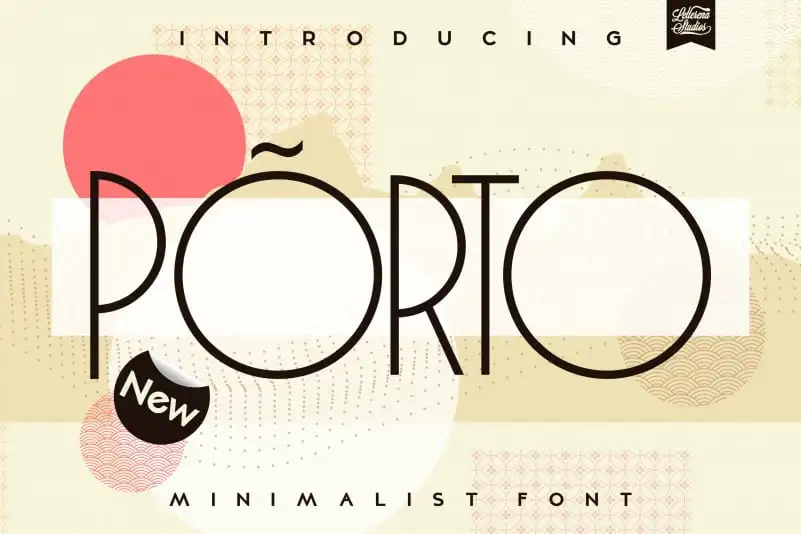
A Porto Display Font é uma escolha perfeita para quem busca um estilo moderno e clean no design de sem-serif. Ela traz letras leves e agradáveis ao olho, com uma aparência muito arredondada que se assemelha mais às serifas do que aos verdadeiros sem-serais. Com sua textura limpa e fina, essa fonte tem um toque suave que permite destacar seu conteúdo de maneira sofisticada. Os criadores da letra, a Letterenastudios, certamente não poderiam ter previsto o sucesso dessa fonte em qualquer projeto gráfico. Seja ela usada em design web, impressão ou aplicativos móveis, Porto Display atingirá um público imenso graças à sua facilidade de leitura e capacidade de se adaptar a diferentes ambientes de uso. Aventura-se neste sem-serif que não apenas combina elegância com simplicidade, mas também é uma peça perfeita para quem busca um design visual moderno e versátil. A Letterenastudios criou algo novo, algo que se sobressai e faz diferença em qualquer projeto onde for usada. Seja você um designer ou artista digital, Porto Display será uma ótima adição ao seu arsenal de fontes de sem-serif para trabalhos profissionais e personalizados.